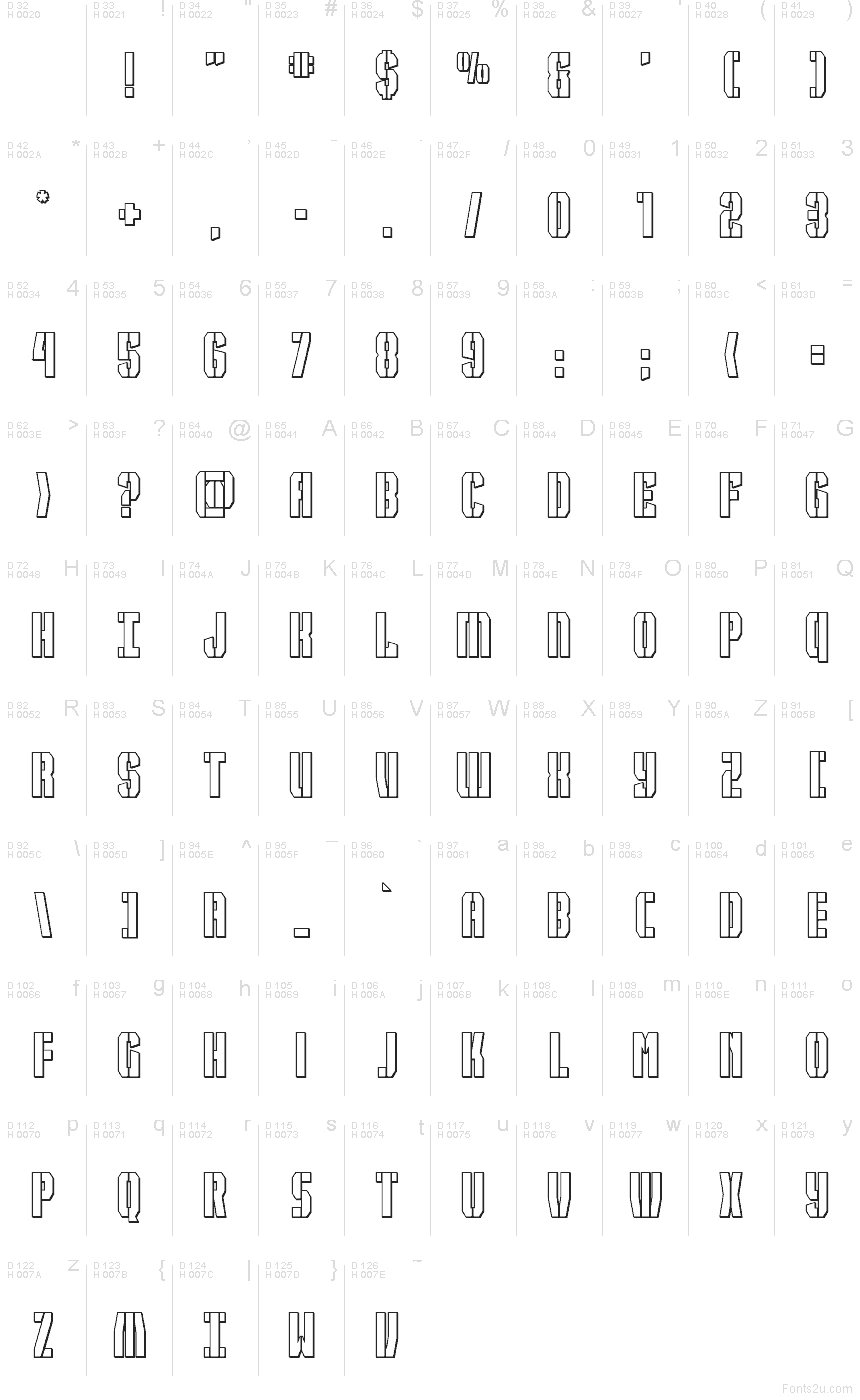
Gorilla Warfare 3D de Iconian Fonts es una tipografía 3D de estilo militar gratuita, que captura la actitud agresiva de las insignias de estarcido llevadas a una perspectiva geométrica y robusta. Sus letras son altas, angulosas y cuadradas, con esquinas recortadas y un efecto dimensional incorporado que otorga a las mayúsculas un ritmo firme y blindado.
Encaja perfectamente en pósteres, pantallas de títulos de juegos, portadas de películas de acción, identidad visual de equipos y folletos de eventos donde se requiera una voz ruda y regimentada. Como fuente gratuita, también funciona muy bien en titulares cortos, experimentos de logotipos y monogramas, ya que esa profundidad cincelada le da a incluso unas pocas letras una fuerte sensación de masa.
Gorilla Warfare 3D